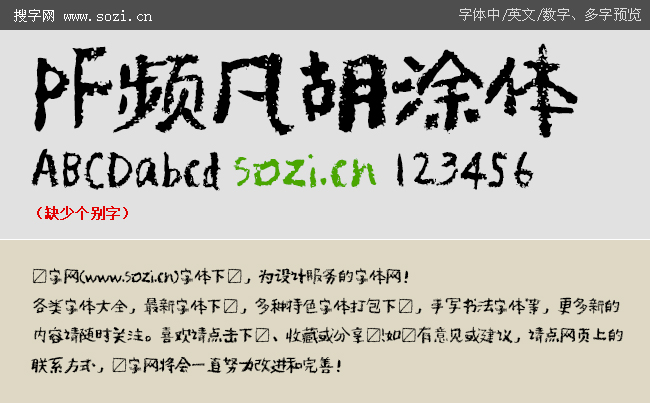
PF頻凡胡涂體
搜字網(wǎng)給大家提供一款PF頻凡胡涂體中文字體下載,PF頻凡胡涂體是一款充滿文藝氣息的手寫(xiě)涂鴉字體,是作者頻凡基于一款日文粉筆風(fēng)格字體增補(bǔ)而來(lái)的,目前仍在增補(bǔ)中,該字體彌補(bǔ)了中文免費(fèi)粉筆風(fēng)格字體的空白,支持免費(fèi)商用。適合應(yīng)用于藝術(shù)設(shè)計(jì)、平面宣傳設(shè)計(jì)、網(wǎng)頁(yè)設(shè)計(jì)、海報(bào)設(shè)計(jì)等應(yīng)用。